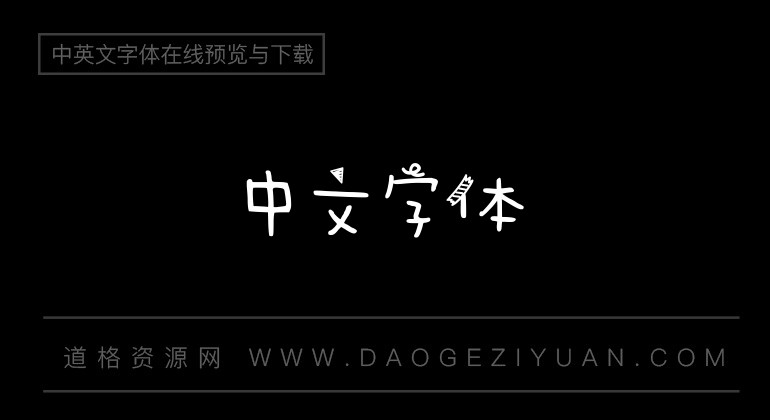
管家纸胶带是一种新型的纸胶带,它由一种特殊的墨水涂层而成,可以将文字、图案等印刷在纸上,使字体更加清晰、易读。它的优点是不易污染,耐久性强,可以抵抗外界环境的侵害,使字体更加清晰易读,而且可以抵抗湿度、温度的影响,更能抵抗腐蚀,使字体更加清晰易读。文件名:ZiTiGuanJiaZhiJiaoDai-2.ttf
字体管家纸胶带是一款非常不错的手写艺术字体,具有很好的视觉感,适合于文化类的宣传设计、商业类品牌的广告和产品包装设计以及个性化文字排版等较多场景。